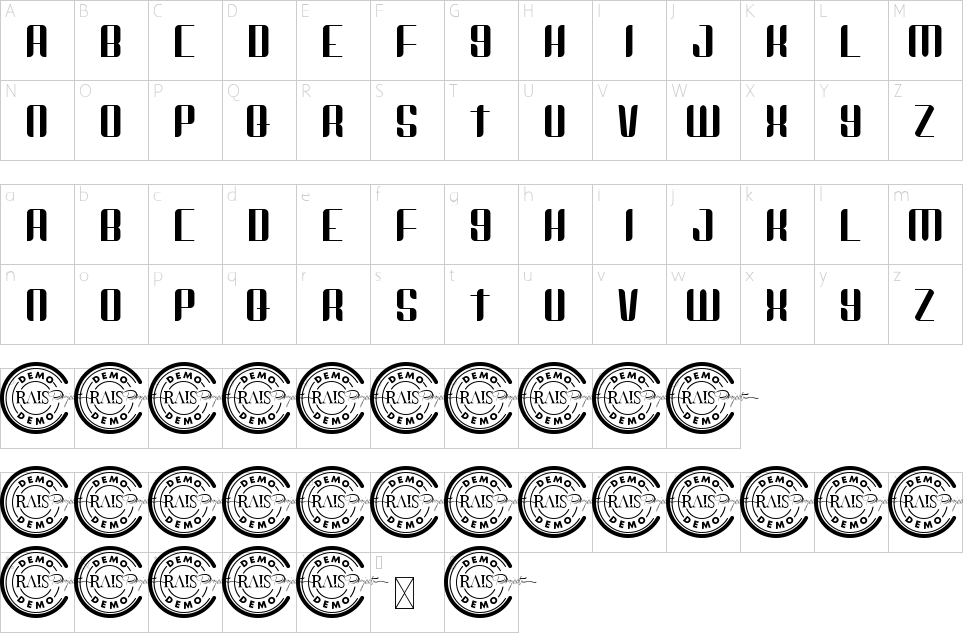
Micronium é uma fonte curiosa e elegante projetada pela equipe do RaisProject, disponível gratuitamente tanto para Windows quanto para Mac. Esta fonte ganhou popularidade entre os designers devido a sua simplicidade e facilidade de uso, sendo facilmente personalizável para diferentes aplicações, desde pequenos detalhes de texto até grandes títulos. Embora a fonte não seja criada por um único designer, é o trabalho conjunto que o torna tão atraente e versátil. Com seu estilo minimalista, Micronium é perfeito para criar ambientes gráficos contemporâneos e modernos, tornando-a uma excelente opção para qualquer designer de gráficos que busca estilização única e simples. Como uma fonte de recursos gratuitos, Micronium oferece um incrível valor aos designers, permitindo-lhes explorar e experimentar novos estilos sem precisar gastar dinheiro.